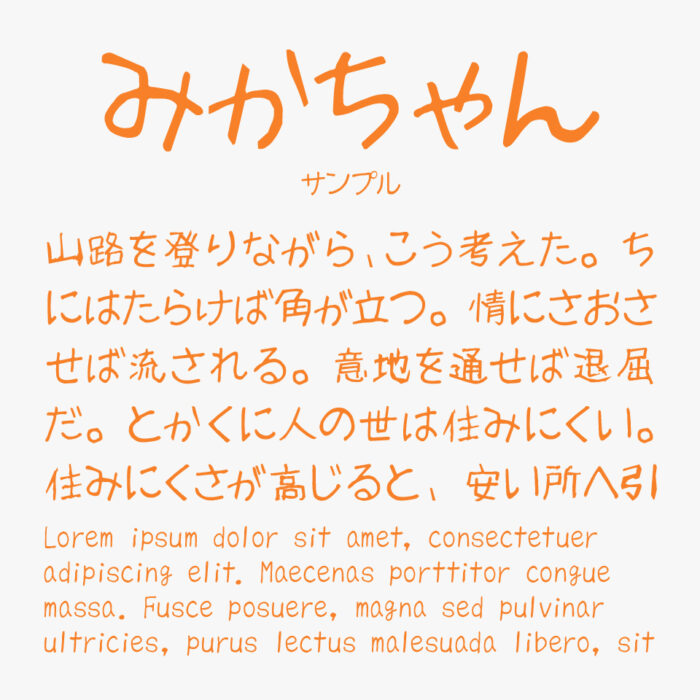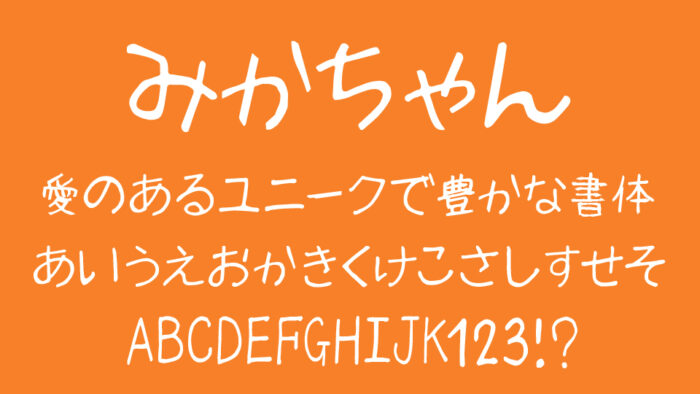
みかちゃんフォントは、少し跳ねたような元気な手書き文字で、無邪気さや素直さが滲み出るような愛らしい手書きフォントです。
2000年初頭に公開されたフォントで、ほどよいラフさがあるリアルな手書き感で、昔から人気の高い手書きフォントです。
収録文字は、漢字(第一水準漢字・第二水準漢字)・ひらがな・カタカナ・アルファベット・数字・記号が収録されています。